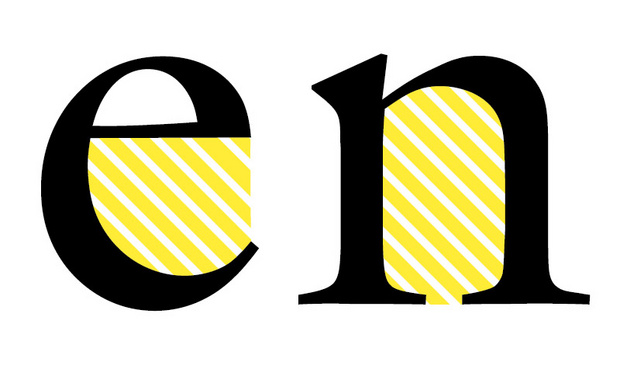
Nicht Punze, sondern ... Aperture?
Ich suche den dt. Begriff für die nichtdruckenden, teilweise von Bögen eingeschlossenen Buchstabenbereiche. Im Englischen heißt der Fachbegriff »aperture« (The Typographic Desk Reference). Gibt’s dafür eine hiesige Übersetzung?
Ich fürchte, das ist auch schon Englischen schwammig. Wörtlich heißt es ja sowas wie »Öffnung« und so würde ich es auch benutzen: http://www.fontshop.com/education/pdf/typeface_anatomy.pdf
Also nicht bezogen auf die Fläche, sondern auf die Größe der Öffnung der Punze/des Binnenraums.
Aber wenn ich jetzt gerade danach google finde ich auch jede Menge Beispiele, wo damit jede »offene Punze« gemeint ist.
In »Anatomie der Buchstaben« wird diese Öffnung der Punze zugeschlagen (»Punze (Counter): teilweise oder vollständig eingeschlossene Binnenfläche«). In keinem deutschsprachigem Fachbuch, das ich zur Hand genommen habe, gibt es einen eigenen Begriff wie aperture. Ich bleibe dann der Einfachheit halber erst mal bei Punze mit Öffnung.
Vielleicht sollte man sich vor Augen führen, woher die deutschen Begriffe für diese Teile eines Buchstabens eigentlich kommen.
Sie stammen in der Regel aus der Zeit in der man die Stempel noch von Hand aus einem Stück Stahl Geschnitten hat. (Wobei ich mir persönlich kaum vorstellen kann, welch eine unglaubliche Mühe es macht, den kompletten Buchstaben Satz einer Diamant, brillant oder Nonplusultra (4,3 oder 2 Punkte Schrift) von Hand zu schneiden)
Hierbei war es natürlich einfacher aus dem Stück Eisen die außen Konturen zu schnitzen, als in die Stirnfläche des Stempels Vertiefungen hinein zu graben. Also hat man mit dem Innenformen der Buchstaben, die ja auch bei mehreren Buchstaben wiederkehren (zum Beispiel n und h) quasi negative Stempel geschnitten und gehärtet, die man dann in den eigentlichen Buchstabenstempel einschlagen konnte. Hierbei spielt es natürlich keine Rolle, ob dieser Innenraum anschließend aufgeschnitten wird oder vollständig umschlossen bleibt. Eine Punze bleibt eine Punze, wie dieser Hilfsstempel bezeichnet wird, der in etwa einem Körner entspricht.
Der "Zwischenraum"   von einem  n  wird Binnenraum genannt. Er zählt nicht zu den Punzen da er nicht umschlossen ist. Binnenraum kann man am Einfachsten mit einem U erklären. Ein Schiff kann im Binnenraum des U eine Wende fahren. So wurde mir es beigebracht, so steht es in der Fachliteratur die mir in die Hände gekommen ist.
„… Punzen heißt man die Leerräume innerhalb des Buchstabenbildes, weil der Stempelschneider ihre Form und Größe ursprünglich durch das Einschlagen eines Stahlstiftes (einer Punze) bestimmt hat …“
(Quelle: Das Setzerlehrbuch von Josef Käufer, Otto Blersch Verlag, Stuttgart, 1956)
Weiß ich nicht wo ich es gelesen habe. Aber ich habe gelesen das Binnenräume/Binnenformen keine Punzen sind. Sie wurden früher zwar auch mit dem gleichnamigen Werkzeug erzeugt, aber sie heißen nicht so. Keine Ahnung wo ich das gelesen habe.
Hätte nicht gedacht das es nur eine Begrifflichkeit ist. Also lag ich mit meiner eigenen Überzeugung doch richtig, als man mir damals erklärte das ein Binnenraum keine Punze sei. Doppelt belehrt - dann doch noch richtig belehrt.
Der "Zwischenraum"   von einem  n  wird Binnenraum genannt. Er zählt nicht zu den Punzen da er nicht umschlossen ist.
Belehrt hat dich niemand. Nur die oben zitierte Aussage von dir ist nicht richtig.
Der Binnenraum eines Buchstabens ist eine Punze. Auch wenn ich diesen als Binnenraum bezeichnen kann.
Dies steht nicht im Widerspruch zu dem von Ralf zitierten Artikel.
Übrigens auch in neuen Fachbüchern wird der Binnenraum eines Buchstaben als Punze bezeichnet.
„Punze (Counter): teilweise oder vollständig eingeschlossene Binnenfläche.“
Karen Cheng, Anatomie der Buchstaben, Verlag Hermann Schmidt Mainz, 2005:
Ja und weil diese Aussage falsch war / ist, wurde ich belehrt in dem ihr mir das klar gestellt habt. Oder bin ich jetzt voll von Sinnen?